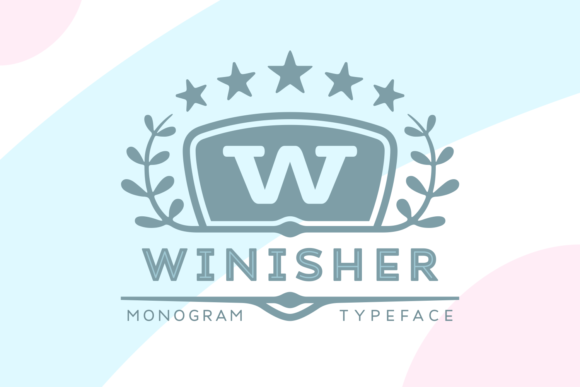
Winisher
Si buscas recursos de alta calidad como Winisher, este paquete premium es una opción fantástica para tus proyectos creativos.
Ya sea que estés creando productos POD (impresión bajo demanda), invitaciones de boda o gráficos para redes sociales, Winisher es una opción ideal.